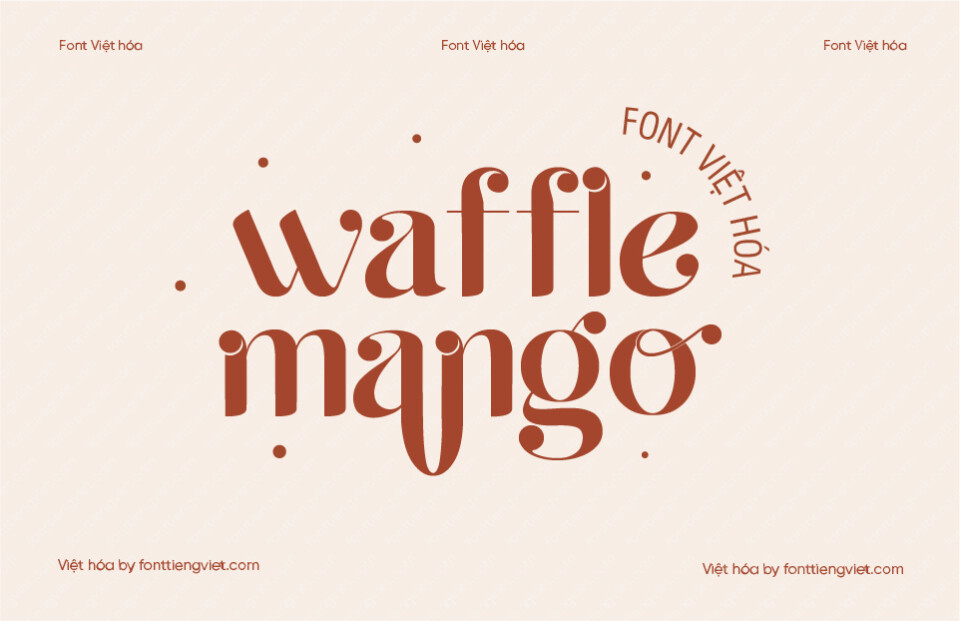
Font Việt hóa 1FTV VIP Waffle Mango
Giới thiệu về Font Việt hóa 1FTV VIP Waffle Mango
Trong thế giới thiết kế đồ họa hiện đại, việc lựa chọn một bộ Font Miễn Phí chất lượng đóng vai trò then chốt tạo nên sự khác biệt. Font Việt hóa 1FTV VIP Waffle Mango là một lựa chọn hoàn hảo dành cho những ai yêu thích phong cách ngọt ngào và trẻ trung. Với đường nét mềm mại mô phỏng hình ảnh chiếc bánh quế mang hương vị xoài rực rỡ, bộ chữ này mang lại cảm giác thân thiện và vô cùng bắt mắt. Đây là sản phẩm được tinh chỉnh kỹ lưỡng về dấu tiếng Việt, giúp các bạn học sinh và giáo viên dễ dàng ứng dụng vào bài giảng hoặc dự án sáng tạo cá nhân mà không lo lỗi hiển thị.
Ưu điểm nổi bật của Font Việt hóa 1FTV VIP Waffle Mango
Thiết kế độc đáo và sáng tạo
Điểm mạnh nhất của Font Việt hóa 1FTV VIP Waffle Mango chính là sự kết hợp giữa tính nghệ thuật và khả năng đọc hiểu tốt. Các ký tự được thiết kế với độ dày vừa phải, bo tròn các góc tạo sự gần gũi. Kiểu chữ này cực kỳ phù hợp cho các tiêu đề sách, thiệp mời, hay trang trí không gian lớp học thêm sinh động. Đặc biệt, bảng mã Unicode được tối ưu hóa giúp font tương thích tốt trên nhiều phần mềm đồ họa phổ biến hiện nay.
Ứng dụng đa dạng trong giáo dục
Đối với các nhà thiết kế trẻ, bộ font này giúp hiện thực hóa những ý tưởng về bao bì bánh kẹo hoặc poster sự kiện trường học. Nhờ phong cách năng động, nó khơi gợi cảm hứng sáng tạo và năng lượng tích cực cho người xem.
Kết luận về bộ chữ Waffle Mango